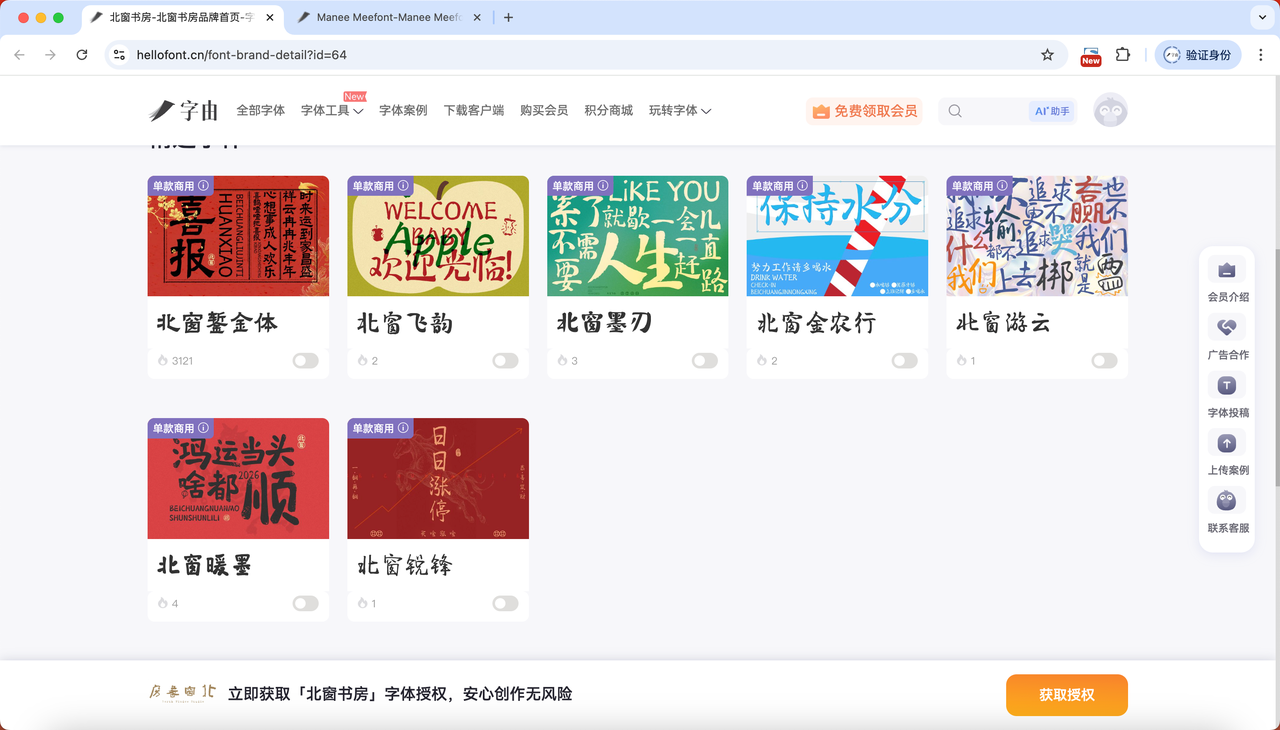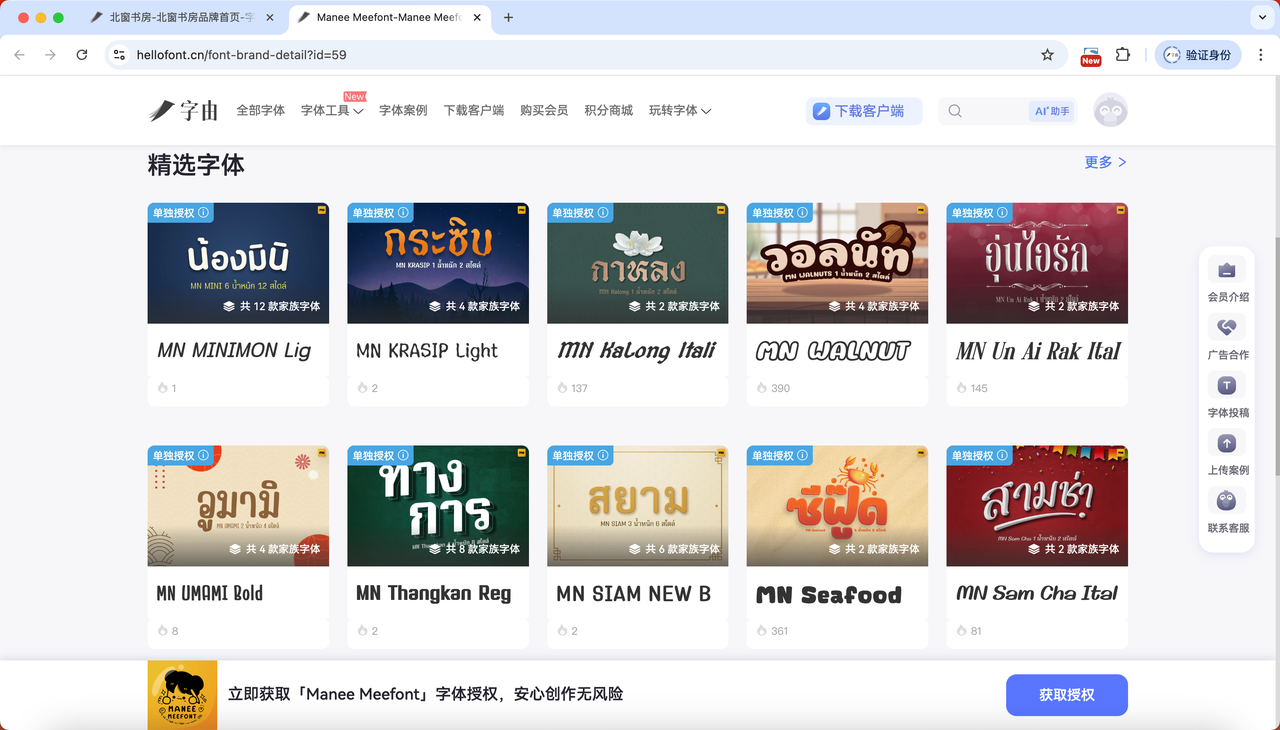
字由字体商城新字库品牌入驻:“北窗书房”与“Manee Meefont”
近日,字由与新生代中文字库品牌 “北窗书房” 及泰文人气字体品牌 “Manee Meefont” 达成深度合作。
两大品牌旗下多款精选字体已全面上线字由字体商城,分别引入多款书法字体与泰文字体,进一步丰富平台字库生态,为设计师提供更广阔的文字创意选择。
字由&北窗书房:以笔墨为窗,照见汉字之美
北窗书房成立于2023年秋,由三位书法硕士共同发起。品牌秉持“篆隶为本”的书法观,溯源古法、融通今意,致力于将传统书法的精神脉络引入当代字体设计。其字体风格兼具古典韵味与现代适用性,如已上架的 “北窗錾金体”“北窗飞韵”“北窗墨刃” 等,在笔触间传递着“落笔成窗,照见期待”的文人意趣。
字由&Manee Meefont:泰式手写风情,点亮异域设计
“字里行间尽是泰式风味”, Manee Meefont是一家专业泰文字体商店,以丰富的手写风格著称,字体涵盖可爱简约至清爽实用等多种类型,适用于日常设计、社交媒体及品牌项目。此次上架的 MN MINIMON Lig、MN KRASIP Light、MN KALONG ITALI 等系列,以其灵动活泼的笔触与鲜明的泰式美学,为跨文化设计注入新鲜活力。目前,该品牌已有 187款字体 入驻字由,成为平台泰文字库的重要组成。